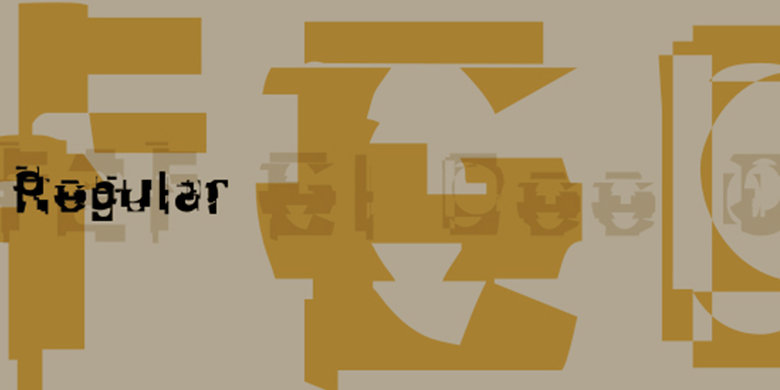
20世纪90年代中期的Techno sound,个人电脑以及新的字体创作软件都成为F2F(Face2Face)字体家族的灵感来源。Thomas Nagel和他的朋友们需要创作新颖的不同寻常的字体,这些字体应该在德国领先的技术杂志《Frontpage》中使用。即使是排版时大小最小设置为6pt,布局也几乎无法辨认,孩子们还是能很愉悦地阅读并解读这些信息。
F2F EI Dee Cons 是Linotype中包含的41种Face2Face字体中的一种。Nagel自己设计了九个。”
The Face2Face (F2F) series was inspired by the techno sound of the mid-1990s, personal computers and new font creation software. For years, Thomas Nagel and his friends formed a unique type design collective, which churned out a substantial amount of fresh, new fonts, none of which complied with the traditional rules of typography. Many of these typefaces were used to create layouts for the leading German techno magazine of the 1990s, Frontpage. Nagel and his fellows would even set in type at 6 points, in order to make it nearly unreadable. It was a pleasure for the kids to read and decrypt these messages!
F2F EI Dee Cons one of 41 Face2Face fonts included in the Take Type 5 collection from Linotype. Nagel designed nine of these himself.”